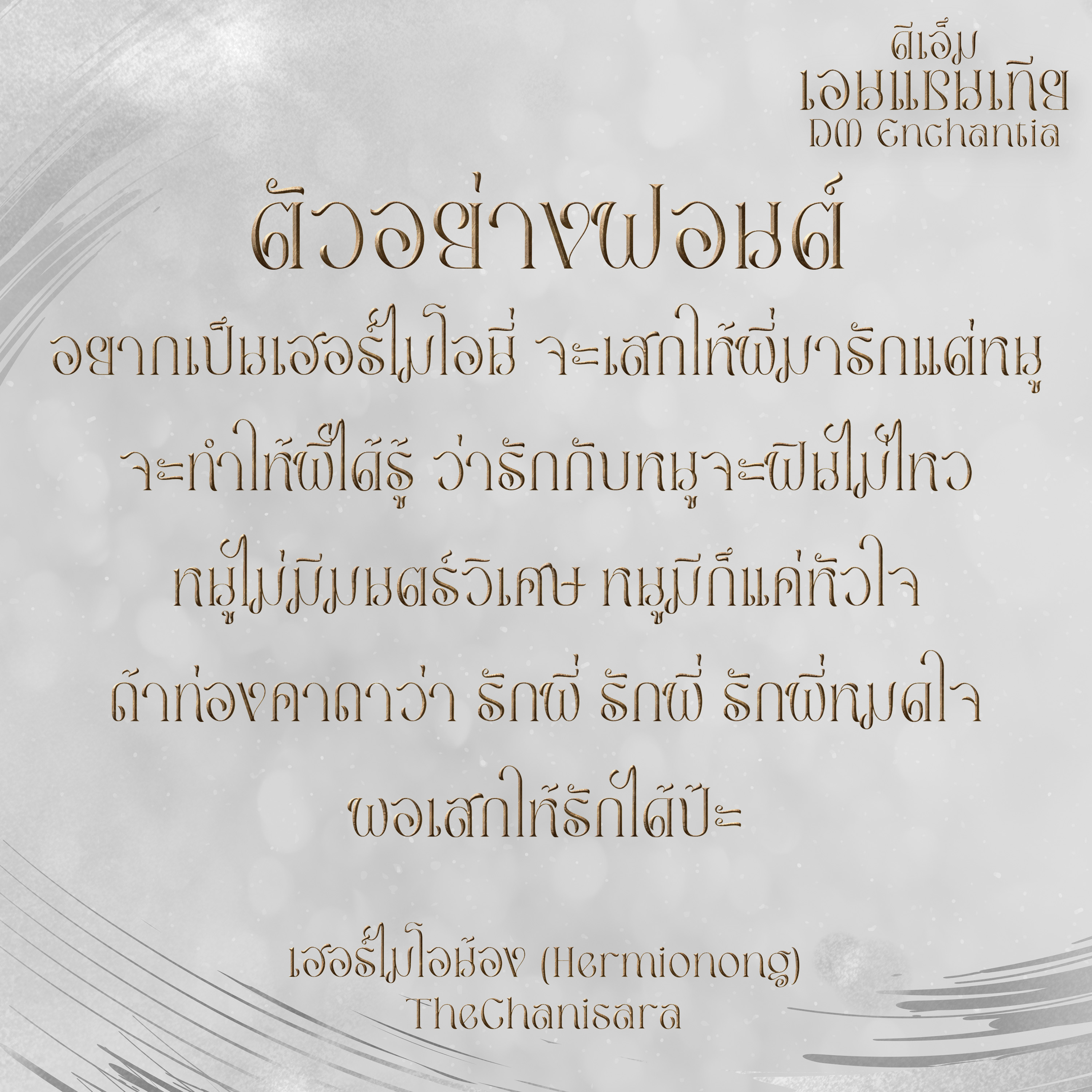
DM Enchantia (ดีเอ็ม เอนแชนเทีย)
ชื่อฟอนต์ : DM Enchantia (ดีเอ็ม เอนแชนเทีย)
ฟอนต์แฟนตาซีผสมกับความเป็นโรมัน ด้วยลายเส้นที่โค้งชวนพิศวงและเคลิบเคลิ้มไปกับมัน